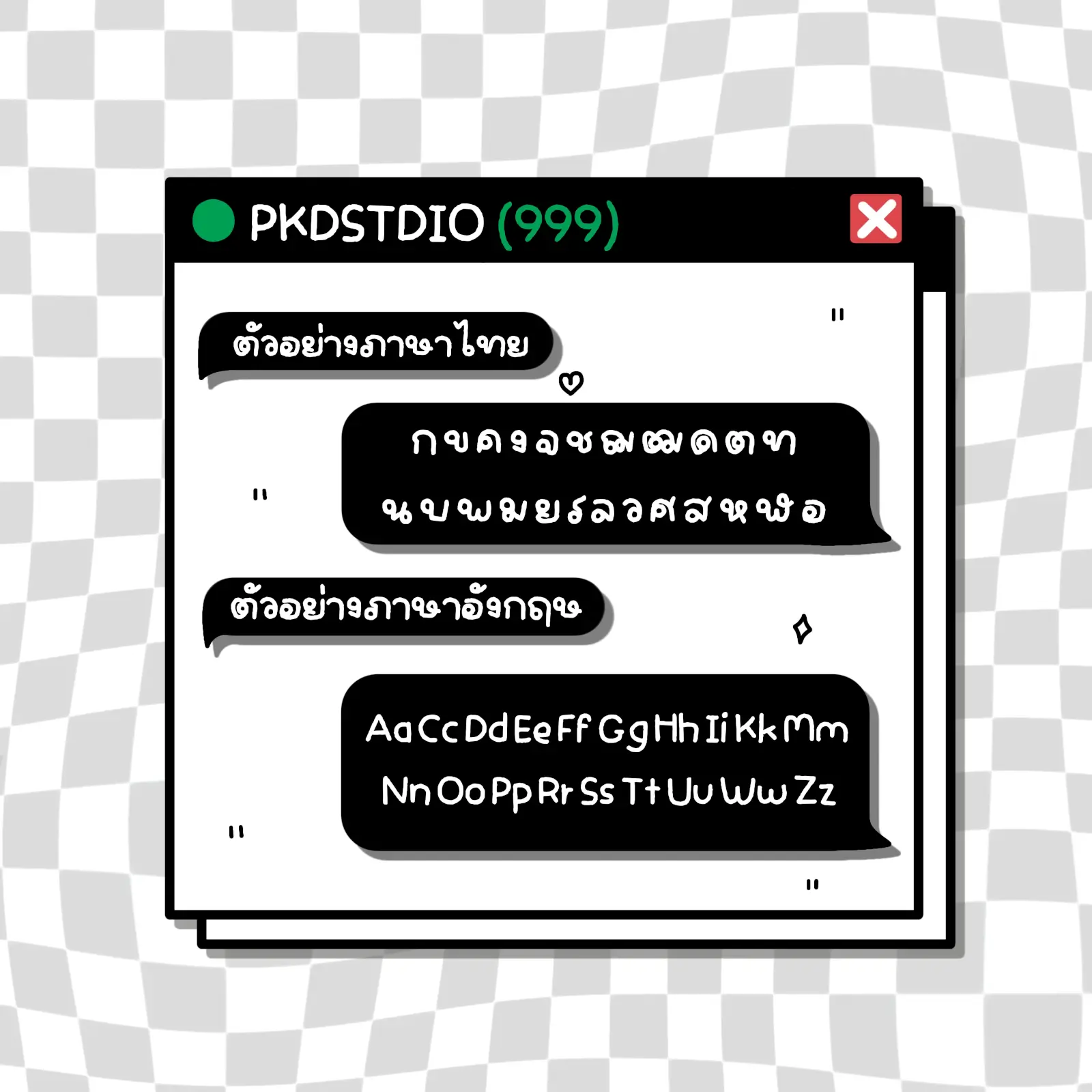
เน็กซ์ฟอนต์ (PKD Next) – ตัวอักษรน่ารัก อ่านง่าย ใช้งานได้ทุกวัน ไม่ว่าจะทำโพสต์ขายของ แต่งคลิป ทำปก หรือออกแบบงานกราฟิกก็สามารถทำได้ง่ายๆ
- รองรับภาษาไทย ภาษาอังกฤษ ตัวเลข และสัญลักษณ์
เน็กซ์ (PKD Next)